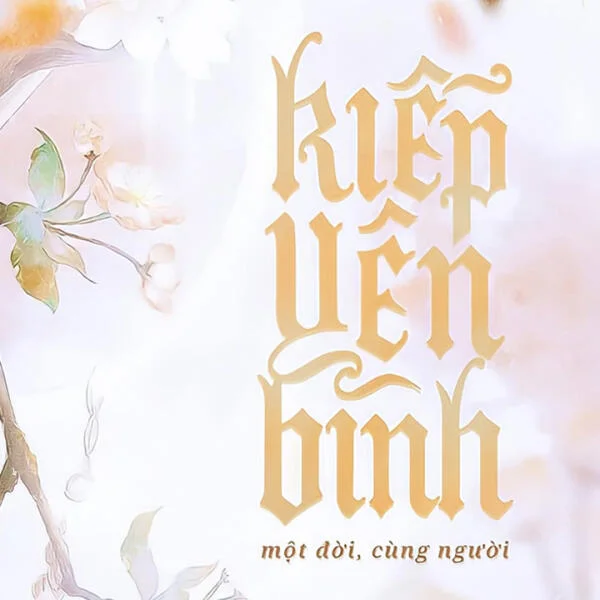
Font Valky việt hóa là kiểu chữ serif cổ điển hiện đại lạ mắt với các chữ ghép đẹp, rất nhiều glyphs thay thế đặc biệt, trang trí và hỗ trợ đa ngôn ngữ. Đây là một phông chữ rất linh hoạt hoạt động hiệu quả ở các kích thước lớn và nhỏ. Hoàn hảo cho các dự án biên tập, thiết kế Logo, Thương hiệu quần áo, bao bì sản phẩm, tiêu đề tạp chí hoặc đơn giản là lớp phủ văn bản phong cách cho bất kỳ hình nền nào.
Tổng quan về font Valky việt hóa
Valky Classic Modern Typeface là một kiểu font serif cổ điển và hiện đại được thiết kế lạ mắt với các chữ ghép đẹp, rất nhiều glyph thay thế đặc biệt. Đây là một font chữ rất linh hoạt ở các text kích thước nhỏ cho đến lớn. Font Valky việt hóa phù hợp cho các dự án xây dựng thương hiệu, tạp chí, bao bì sản phẩm...
Bộ font việt hóa Valky bởi MTD bao gồm 4 kiểu:
- Valky Light
- Valky Regular
- Valky Bold
- Valky Semibold